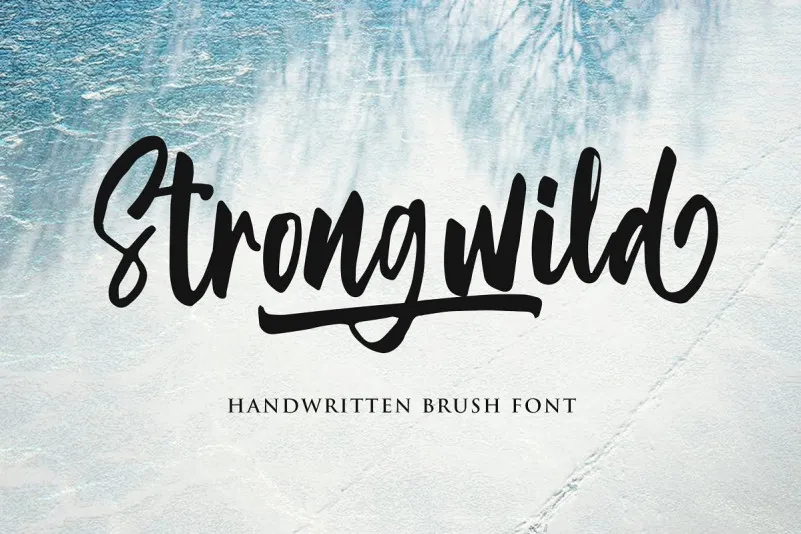
Strongwild Brush Font – Download Grátis
Descubra a fonte Strongwild Brush Font, uma criação inovadora dos designers do Typefar. Esta fonte em estilo script é perfeita para aqueles que buscam algo autêntico e moderno ao mesmo tempo. Ela oferece um aspecto de letra escrita à mão utilizando o velho e confiável instrumento da caneta-pen, garantindo uma consistência única em cada palavra. Ideal para diversos projetos gráficos como impressões em lençóis, camisetas personalizadas ou até mesmo vídeos, Strongwild Brush Font é um recurso versátil que trará o toque pessoal a seus trabalhos. Ela oferece 26 swash (letras desenhadas à mão), adicionando uma espessura única e elegante ao seu design. Com este fonte, você pode dar vida aos seus projetos com um estilo único e distintivo, sem se preocupar em buscar soluções alternativas. Sem dúvida, Strongwild Brush Font é a escolha perfeita para criar experiências visuais memoráveis que destacam sua personalidade única no mundo da design gráfico.